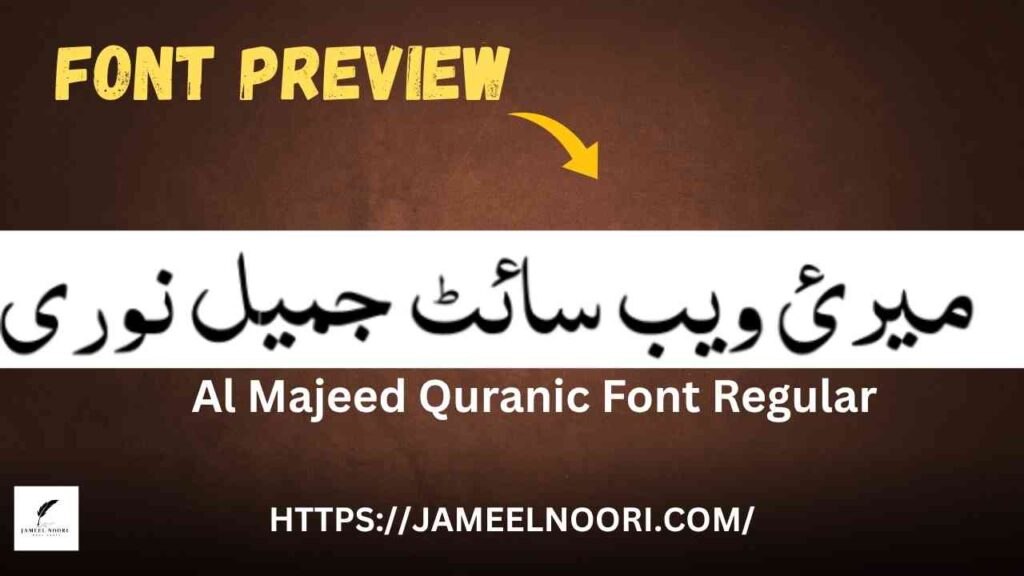
Introduction –Urdu Font Al Majeed Quranic Regular Kya Hai?
Agar aap Quranic Arabic aur Urdu content ke liye ek high-quality aur readable font ki talaash mein hain, to Al Majeed Quranic Font Regular aap ke liye perfect choice hai.. Yeh font specially Qurani Ayaat, Tafseer aur Islamic content ke liye design kiya gaya hai.. Ab tak is font ko 68,188 dafa download kiya ja chuka hai, jise 61 users ne 3.54/5 ki average rating di hai..
Urdu Font Al Majeed Quranic Regular Ke Features
• Quranic Style Arabic aur Urdu support
• ✅ Ideal for Quranic text, translations, aur Islamic books
Al Majeed Quranic Font Ka Istemaal Kahan Kiya Jaye?
Yeh font un Islamic scholars, designers, aur students ke liye hai jo religious content ko asli Qurani naqsh mein pesh karna chahte hain:
• 📖 Quranic Ayaat ka tarjuma ya tafseer likhne ke liye
• 🕌 Islamic posters aur banners
• 📚 Madaris ke syllabus ya kitaabein
• 🧾 Arabic duain aur wazifa books
• 🖥 YouTube Islamic videos ke thumbnails ya lower thirds
❓ Kya yeh font Arabic aur Urdu dono ko support karta hai?
Bilkul, yeh font Arabic script aur Urdu dono mein achi tarah kaam karta hai..
Conclusion – Apne Islamic Content Ko Khubsurat Banayein
Al Majeed Quranic Font Regular ek aisa font hai jo Quranic beauty aur Arabic elegance dono ko combine karta hai.. Islamic content, research papers, ya religious posters ke liye yeh font aapka pehla intekhaab hona chahiye.